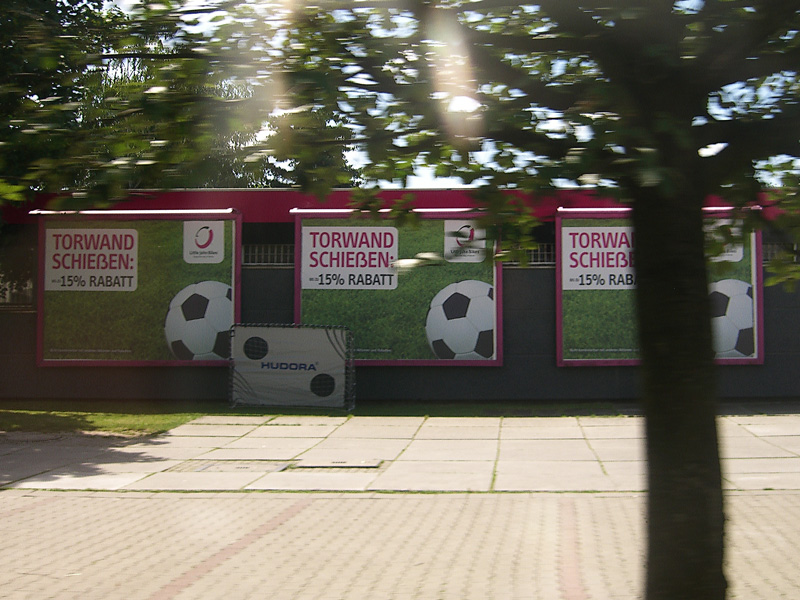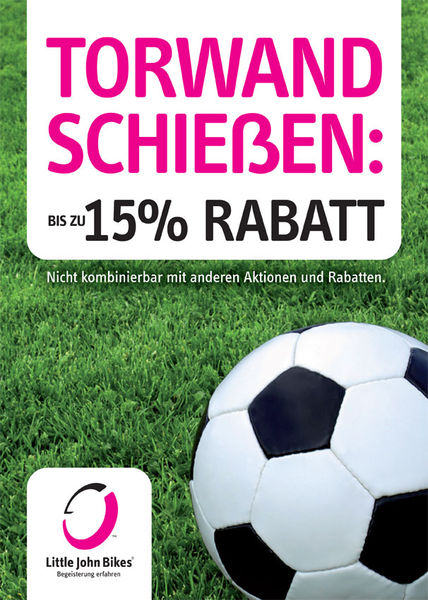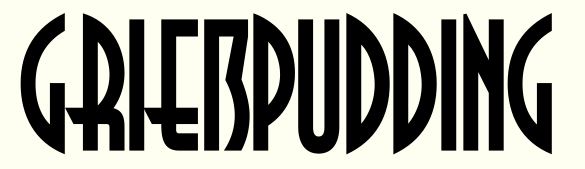
Kuckt euch das mal an:
Gibt’s auch (aktuell) hier nochmal in ordentlich:
Die Schrift ist wohl die FF Info Display – und es ist kein kleines ß.
Da scheint sich wohl jemand selbst ein bisschen beholfen zu haben, da die FF Info Display meines Wissens nach standardmäßig kein Versal-ß parat hat. (Jedenfalls kommt da nix in den Online-Vorschauen.)
Schön, dass da scheinbar jemand Spaß dran hatte – ich finde es allerdings doch leider ein wenig zu unhübsch. Gliedert sich nicht wirklich gut in die Reihe der übrigen Majuskelformen ein: zu breit, zu untersetzt, zu viele „schnelle Kurven“, wurstelige Strichstärke …
Was sagt ihr ?
Ich hatte im Strang
Welche Schriftart ist das auf dem Bild ?
ja zur Anna eine Clone-Schrift angegenen, die ich schon Ewigkeiten durch so eine Freefont-Sammel-CD besaß.
OK, die schrift ist zu recht als zweifelhafter Clone bezeichnet, zumal sie schon recht kurz nach erscheinen des Originals nachgehäkelt wurde.
Eines hat mich dann doch überrascht: Das ß sieht etwas anders als in der Originalschrift "Anna" aus, deutlich ein Versal-ẞ - und das 1992!
(hab ich mir grad eben gemacht :-) )
Das liegt am Font, nicht an Myfonts: den beiden (augenscheinlich identischen) ẞ-förmigen Glyphen im Font wurde kein Unicode zugeordnet. Aber eigenartigerweise ;-) sehe ich statt deines Beispielbildes nur »267…555.gif«.